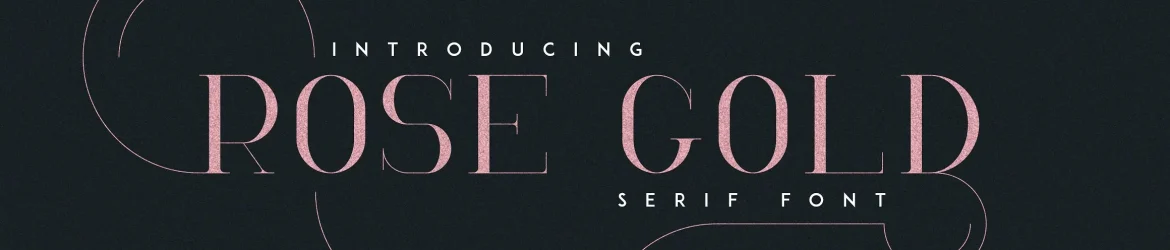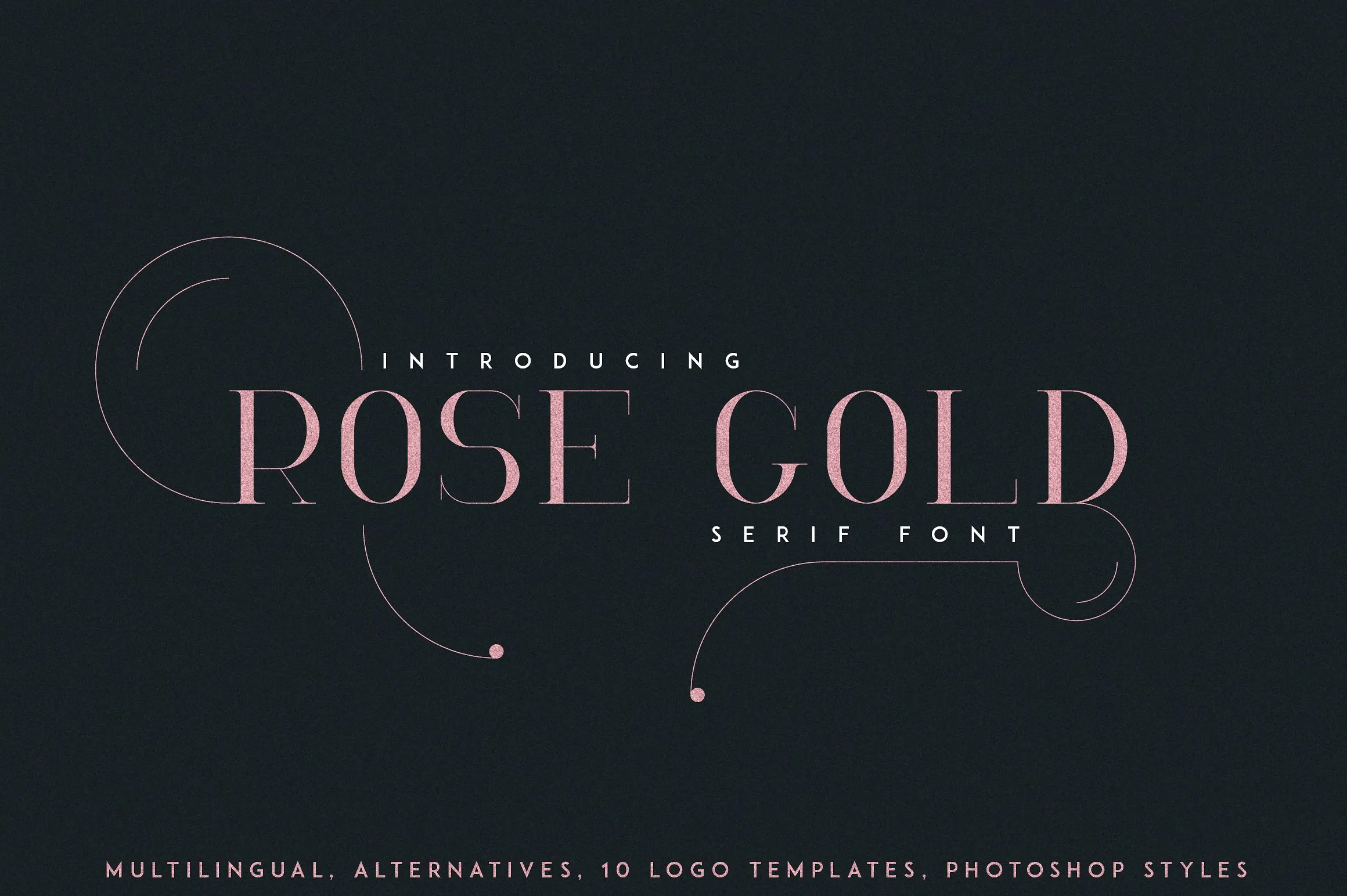
RoseGold Serif Font
A RoseGold Serif é uma tipografia serif que traz alta contraste para tornar suas composições ainda mais atraentes. Ideal tanto para títulos quanto para textos, ela oferece 7 alternativas de caracteres por cada letra, garantindo versatilidade em qualquer tamanho e formato. Este tipo é perfeito para projetos de branding, desde estilos de vida até convites de casamento ou cabeçalhos de revistas. É também uma ótima escolha para um estilo minimalista que complementa qualquer imagem de fundo. Inspirado no metal rosado dourado que tornou-se popular nos últimos tempos, a RoseGold Serif é uma fonte elegante e versátil que se adapta em projetos diversos. Hamilton, o designer desta fonte, criou um modelo para logotipos que combina perfeitamente com esta tipografia. Seja você quem está trabalhando no design de branding, ou simplesmente quer adicionar um toque alegre aos seus projetos, a RoseGold Serif é uma excelente opção. Esta é uma fonte que vale o investimento para qualquer designer gráfico, pois ela não apenas adiciona beleza e sofisticação às suas criações, mas também oferece flexibilidade de uso em diferentes tamanhos e formatos.